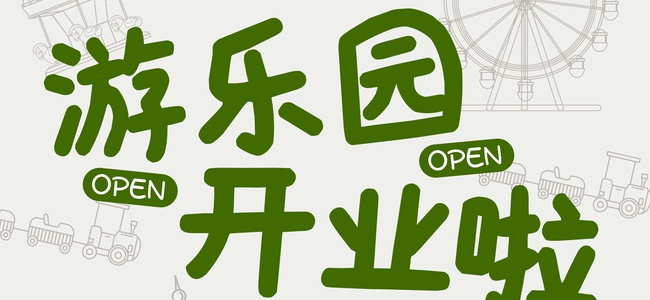
Aa二值圆
字体作者:Aa字库
字体名称:Aa二值圆
字体家族:Aa字库
书体类型:手写/印刷体
Aa二值圆是一款不错的艺术字体,由Aa字库出品,字体笔触适中,字形端正,具有很好的视觉感,适合应用于艺术设计、平面宣传设计、网页设计,书法字帖等领域,需要的朋友可以前来本站下载。
Aa二值圆 - 预览1
Aa二值圆 - 预览2
Aa二值圆 - 预览3
Aa二值圆 - 预览4
Aa二值圆 - 预览5
Aa二值圆 - 预览6
Aa二值圆 - 预览7
Aa二值圆 - 预览8
Aa二值圆 - 预览9
Aa二值圆 - 预览10
Aa二值圆 - 预览13
Aa二值圆 - 预览18
Aa二值圆 - 【大石调】初生月儿
Aa二值圆 - 述怀二十韵献覃怀相公
Aa二值圆 - 奉送李宾客荆南迎亲
Aa二值圆 - 大写字母/小写字母/数字